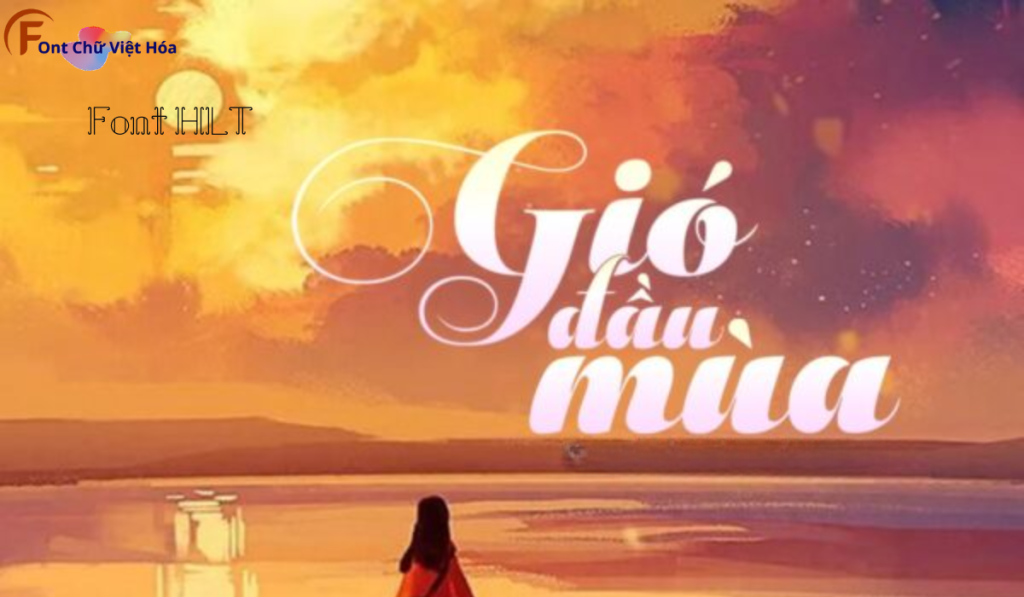
Font HLT Aparo Việt Hóa
Tác giả: HLT Fonts
Font HLT Aparo Việt Hóa là một font chữ không chân cá tính, thuộc bộ font HLT. Được thiết kế với mục tiêu mang lại sự độc đáo và sáng tạo, font này lý tưởng cho các dự án thiết kế như logo, poster, và bao bì sản phẩm. Với các nét chữ sắc nét và độ dày đều đặn, Font HLT Aparo Việt Hóa không chỉ dễ đọc mà còn tạo cảm giác hiện đại và phá cách.